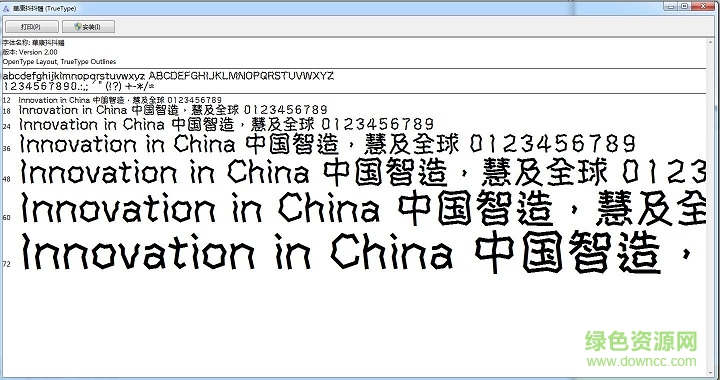
華康抖抖體W5
華康抖抖體W5字體是由綠色資源網(wǎng)小編為大家提供的免費(fèi)字體!這款字體字如其名!看起來很想湖水波動(dòng)的樣子,比較有特點(diǎn)!喜歡的朋友歡迎下載。
華康抖抖體是一款免費(fèi)的簡體中文字體,該字體線條都是抖動(dòng)形狀,但整體效果十分出眾,并且字庫完整,可以適用于名片設(shè)計(jì)、平面設(shè)計(jì)、廣告設(shè)計(jì)、報(bào)紙雜志、企業(yè)LOGO、商標(biāo)注冊(cè)、電視臺(tái)廣告等領(lǐng)域。需要的用戶歡迎在綠色資源網(wǎng)下載使用。
華康抖抖體W5字體